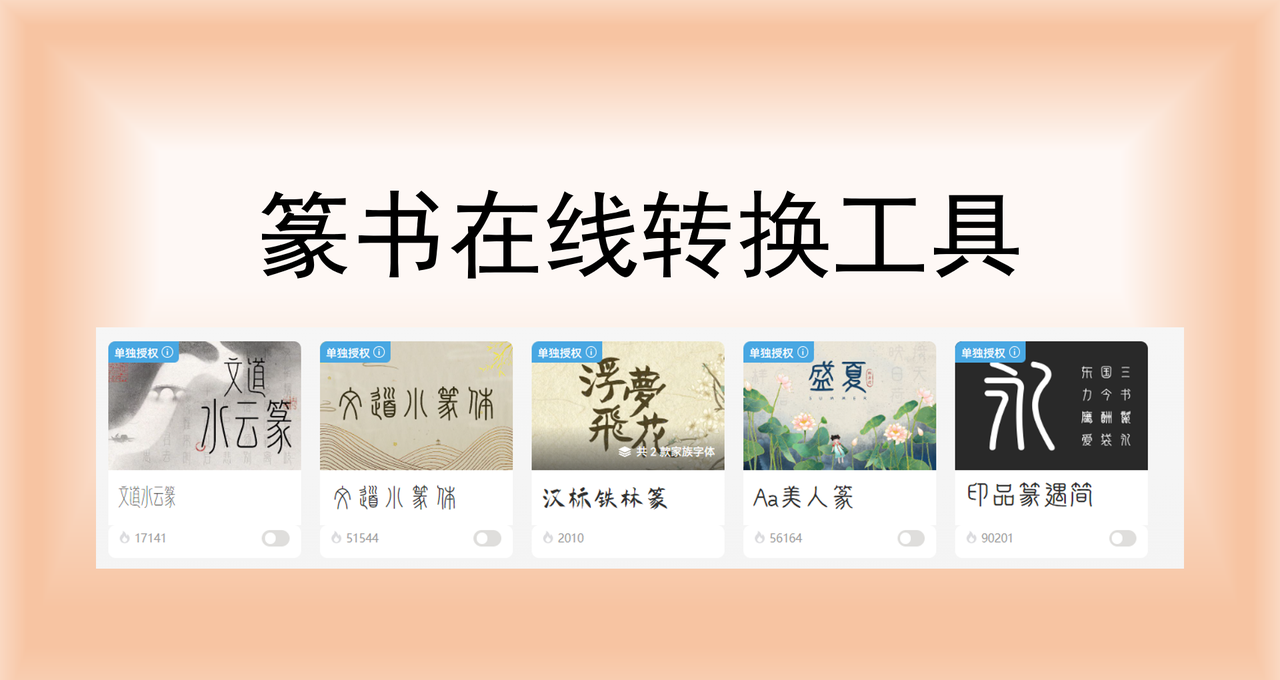
篆书在线转换工具推荐,让你的文字秒变书法
你是否曾在设计文创产品或创作国风海报时,苦恼如何找到韵味十足的篆书字体?总觉得字体不够精美,总觉得自己的作品差了一点精髓?随着互联网技术的发展,市面上已经涌现了多款篆书在线转换工具,无论你是书法爱好者、设计师、新媒体创作者,都能一键获得精美的篆书字体。本文为大家精选了 5 款优质的专属在线转化工具,涵盖国内国外专业级工具,只需要输入文字就可以在线转换成篆书,让你的文字秒变书法!而且这些工具无需下载,打开网页就能在线使用,新手也能轻松拥有专业级的篆体书法!
一、字由
提起字由,很多人肯定都不陌生,这是一款面向设计师用户提供字体应用,管理,授权服务的设计师必备的字体管理神器。字由提供了丰富的字体模板,收录了 5000+ 精选字体,灵活授权方式,满足多样设计需求。其中包含大量专业的篆书字体,涵盖小篆、大篆、印篆等多种风格类型,用户只需要在字由的字体库搜索“篆”即可在线浏览字体效果。如果你想要更直观感受不同篆书的呈现效果,这款工具支持批量预览,可以直接在预览框内输入你想要的文字内容,清晰地对比不同字体,帮助你更快速找到心仪的字体哦。
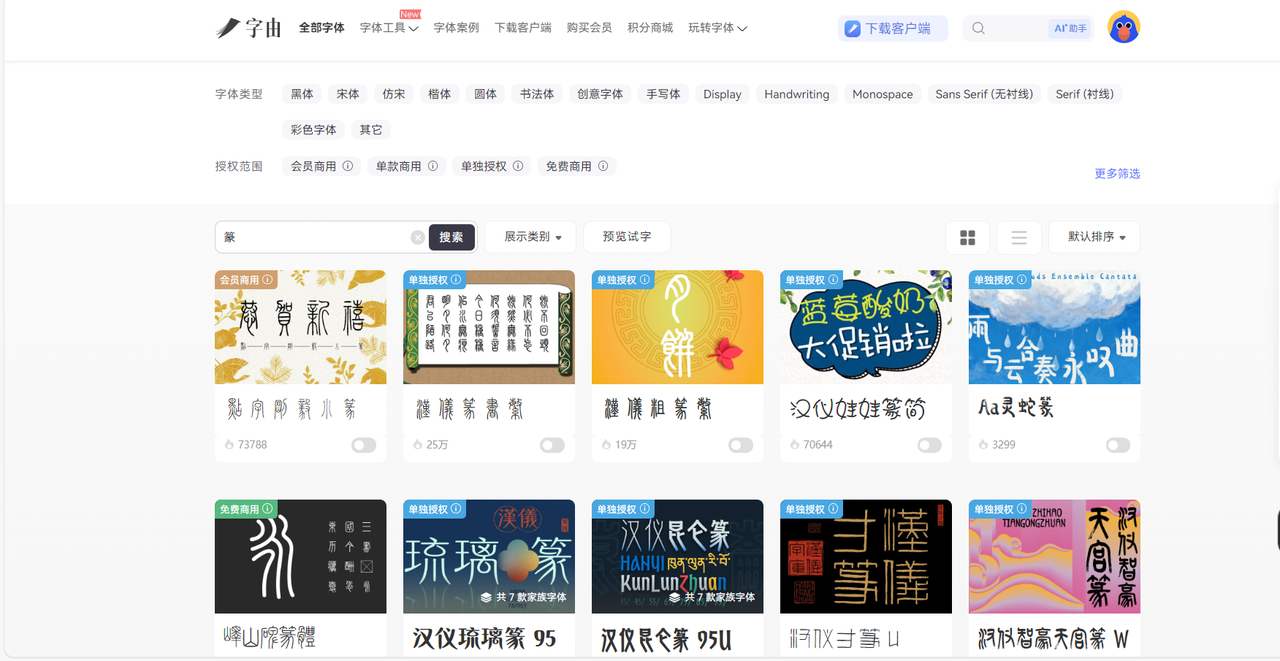
二、Chinese Calligraphy Generator
Chinese Calligraphy Generator 是很典型的中国书法生成器,精准复刻书法的笔墨韵味,内置了楷书、行书、草书、隶书和篆书五种纯正的毛笔书法风格,专注于生成传统书法字体。用户只需要输入一段文字并选择篆书风格,Chinese Calligraphy Generator 运用图像处理技术模拟真实毛笔的写作效果,轻松将文字在线转换篆书字体,生成的每个字都仿佛由书法大家亲笔书写,不仅笔触自然,墨色过渡也非常自然。因此,在国风文创设计、民俗文化展览、古诗词配图等需要浓厚文化氛围的场景而言,这款工具绝对是最优质的选择。与其他转换转换工具不同的是,它在转换字体的过程当中融入了书法美学的考量,最终篆书字体的呈现效果也更加接近传统书写的气质,自带文化古韵与手写温度。
三、Stampdy
在今天的篆书在线转换工具中,Stampdy 是一个与众不同的存在,它将篆书字体和印章设计进行了深度巧妙融合,是一个实用性高的在线印章制作工具。使用 Stampdy 可以轻松创建出带有篆书文字的电子印章,可用于个人姓名章、公司印章、艺术签名、书法作品落款等多种场景中,完美解决了“想要篆体印章却没有实体篆刻”的问题。用户在生成电子印章过程中,可以自由选择圆形或方形的印章,自定义边框粗细、印油效果、文字布局等细节,并且修改完成后可以在线实时预览。最值得一提的是,Stampdy 支持导出 SVG、PNG、PDF、EPS 等多种格式,分辨率最高可达 10 倍,放大也不会损坏画质,完全满足专业打印和数字展示的双重需求。
四、Akuziti
Akuziti 是一款完全免费、无需注册、字体效果多样的篆书在线转换工具,支持将汉字转换成各种艺术风格的字体,涵盖了毛笔字、艺术字、英文字体、花体字、手写字体、pop字体、像素字体、书法字体等风格。Akuziti 上方菜单栏设有篆书字体的分类,进入该页面后还可以看到更细致的篆书选择,例如大篆、小篆、篆刻、反刻等,在文本框输入文字并选择喜欢的字体样式后,系统会自动生成一张 PNG 图片。你还可以自行调整文字颜色、字体大小和背景透明度,导出字体可选择透明背景,便于后续在 PS、AI、Sketch 等设计软件中进一步编辑。整个转换过程不超过 10 秒,操作简单,即使是新手小白也可以尝试用 Akuziti 进行篆书转换,你也体验一把书法大家的既视感。需要提醒大家的一点是,该工具主要还是以转换简体中文为主,大部分复杂的生僻字很难完成在线转换。
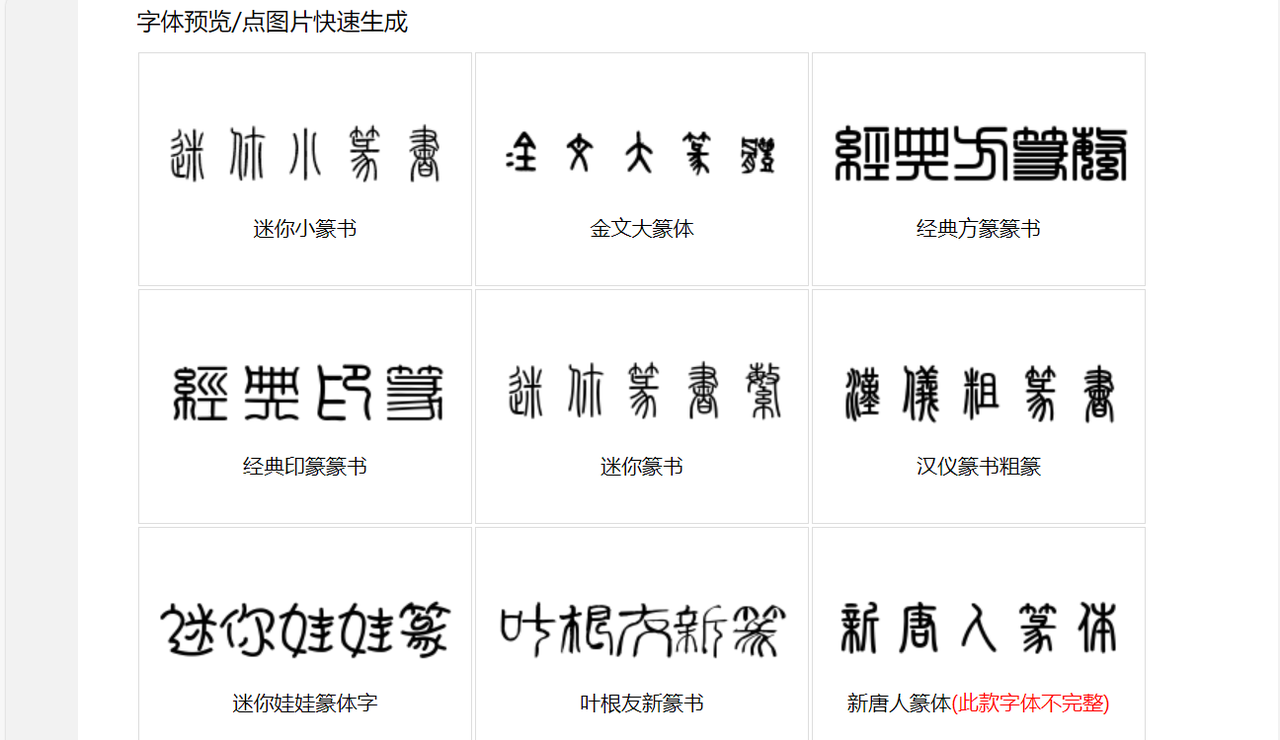
五、Creative Aspirant
Creative Aspirant 集合了多种创意字体工具,最出名的就是内置的篆书字体生成器。用户打开网站后,只需要输入想要转换的文字内容,然后在字体列表中选择“Seal Script”,短短几秒就会获得篆书字体啦,整个过程没有任何多余的步骤,可以说是将篆书字体转换效率提升到了很高的级别。最好用的就是它的实时预览功能,每当你修改文字内容或切换字体样式的时候,预览区域会同步修改,你觉得满意后再点击“生成”按钮即可,对很多需要反复调整文案的设计师来说非常友好。除此之外,Creative Aspirant 还提供了书法毛笔字、水墨字体等多种艺术字的选项,生成字体后还可以进行二次美化,使字体效果更佳逼真且富有设计感。
总的来说,篆书在线转换工具的出现无疑是很多人的福音,无需任何书法技巧也能找到精美且专业的篆体文字。字由拥有海量可商用的篆书字体模板;Chinese Calligraphy Generator 的篆书字体更加逼真有韵味;Stampdy 的特色印章生成功能是一大亮点;Akuziti 提供百种免费艺术字型;Creative Aspirant 操作极简且即时预览效果。每款工具都有它擅长的功能,大家可以根据日常需求来选择最适合自己的工具,让传统篆书的古韵之美继续在数字时代绽放盛开!